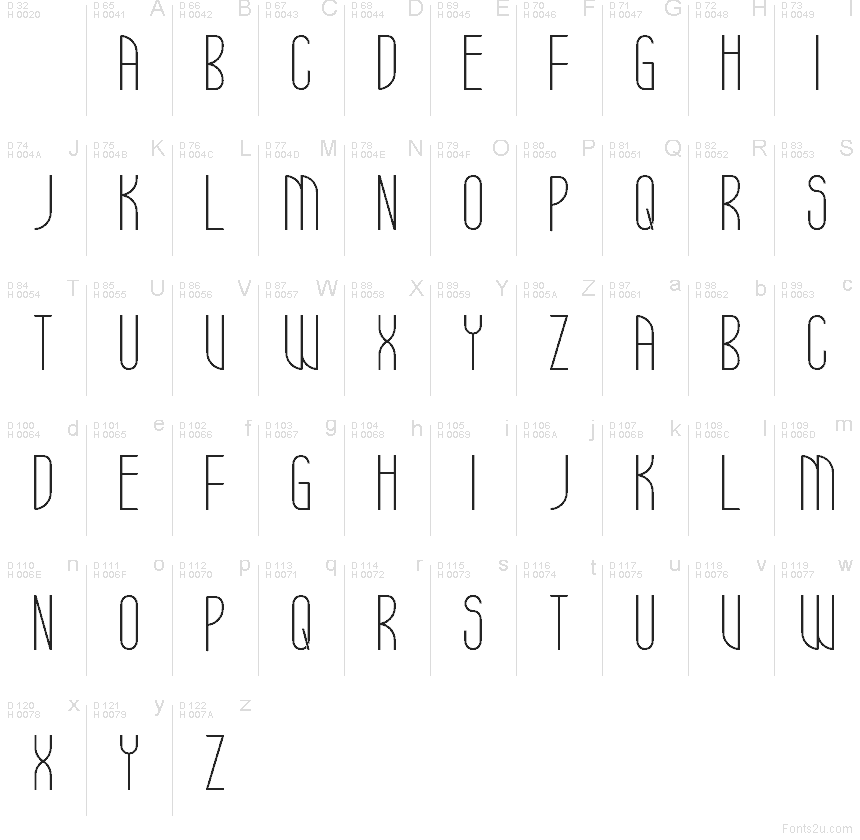
Retro Famous Retro od Vladimira Nikoliče je bezplatné Art Deco display písmo, které definují vysoká, úzká písmena a dlouhé vertikální tahy, dodávající každému slovu elegantní, vzpřímený rytmus. Díky zaobleným rohům a minimalistické geometrii má blíž k historickým nápisům na kinech a výlohách obchodů než k běžným retro stylizacím.
Tato silueta skvěle vynikne na plakátech, v nápojových lístcích, na obalech alb, u butikových obalů nebo při tvorbě firemní identity, kde je potřeba čistý historický nádech bez zbytečných příkras. Písmo také dobře poslouží v titulcích a grafice akcí, protože díky opakující se vertikální struktuře vytváří úhlednou dekorativní texturu i v krátkých řádcích.